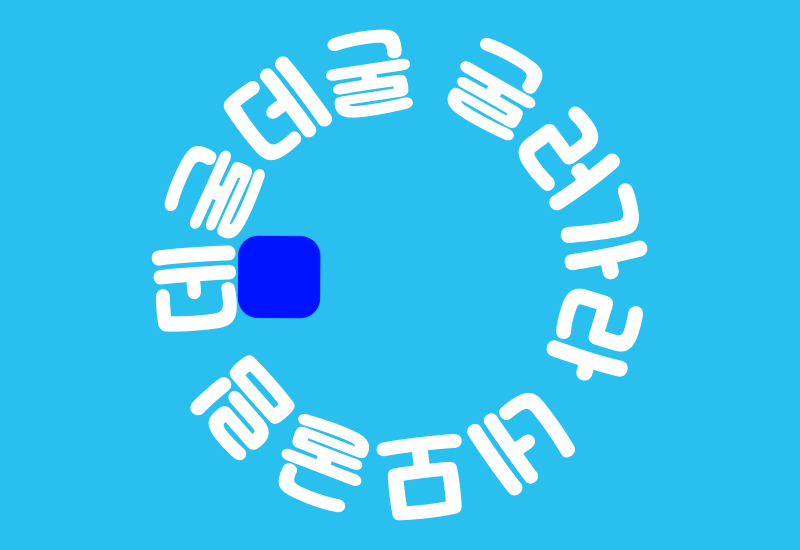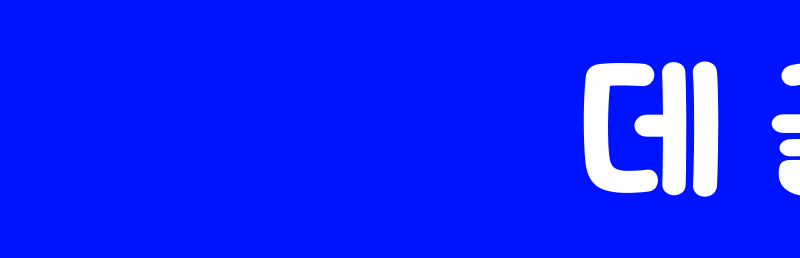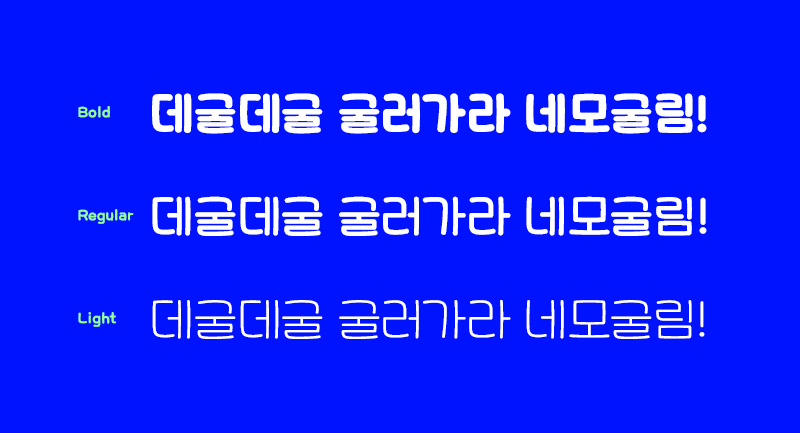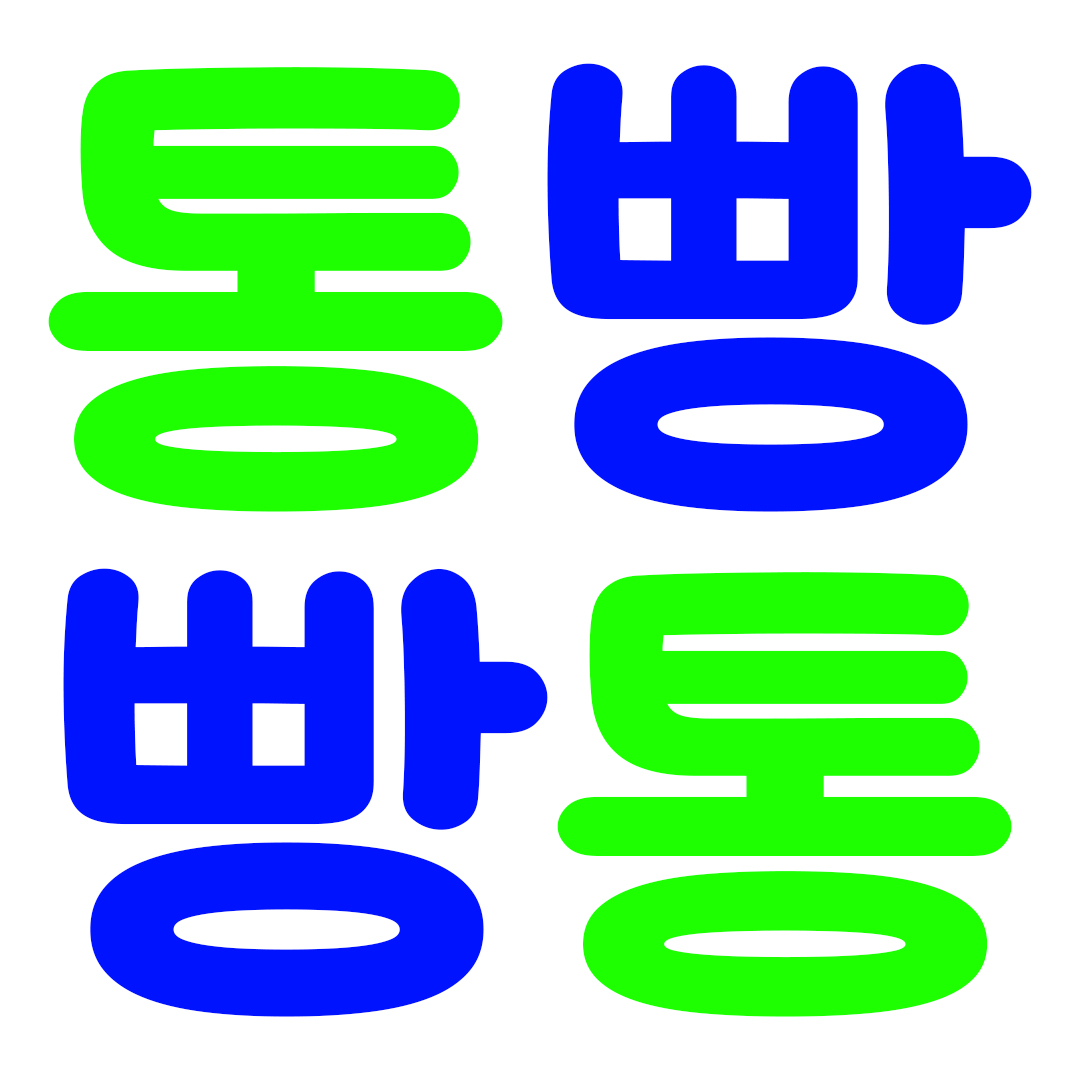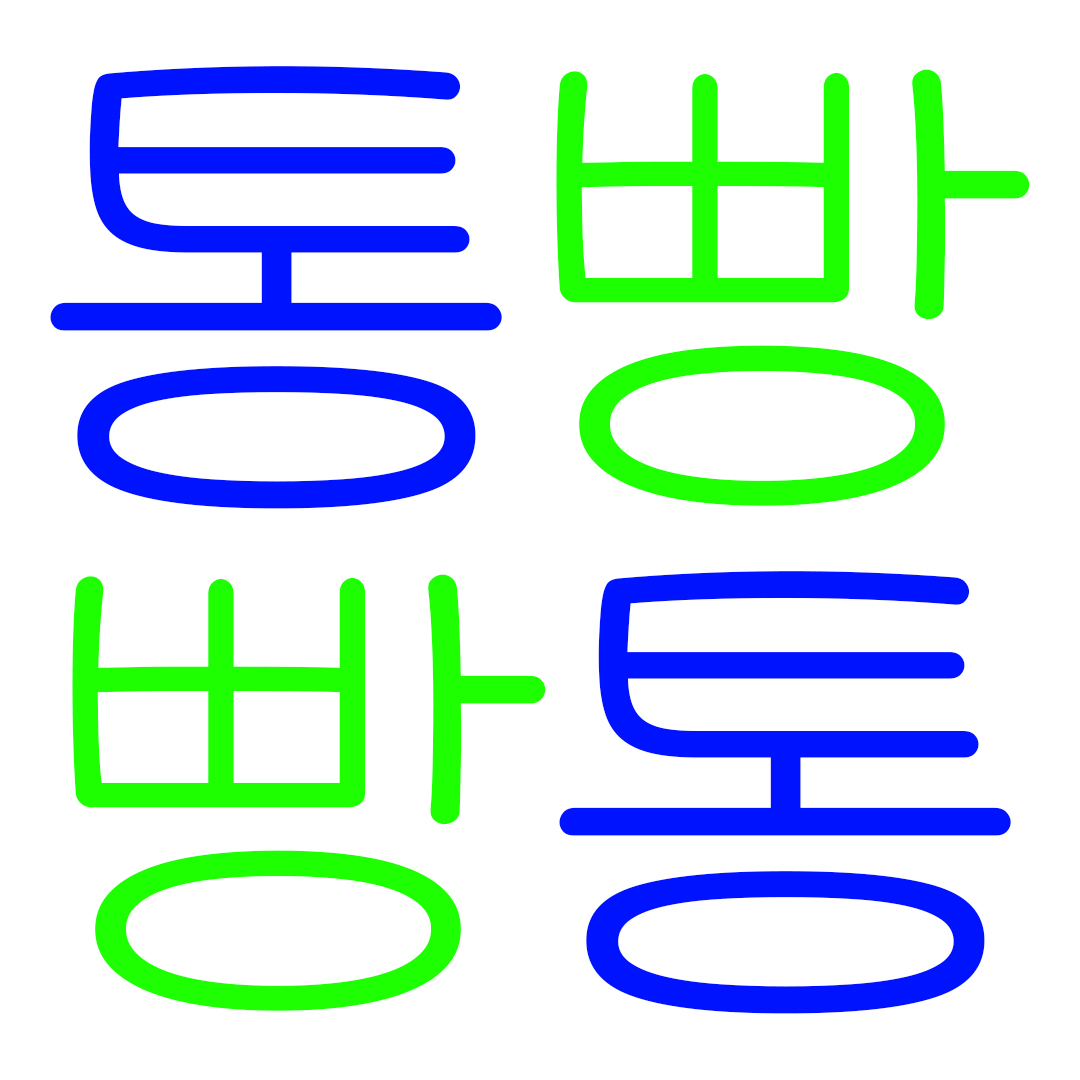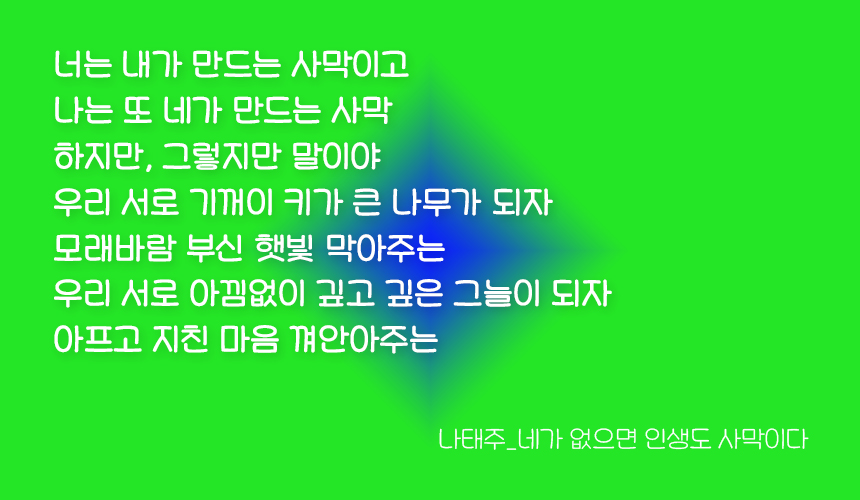
안녕하세요. 정갈한 고딕에 부드러운 굴림을 더한 2월의 신서체, 「Rix네모굴림」을 소개합니다. 데굴데굴 굴러가는 네모의 모습에서 착안해 디자인한 서체인데요, 각이 있는 부분에 굴림을 넣어 전체적으로 텐션이 느껴지는 귀여운 서체입니다. 폰트를 제작한 이수하 디자이너와의 인터뷰를 통해 더 자세히 알아볼게요!
이번에 제작하신 'Rix네모굴림 '서체에 대해 간단히 소개 부탁드려요.
Rix네모굴림은 꽉 찬 사각형 모듈에 데굴데굴 굴러가는 네모의 모습을 상상하며 만든 폰트입니다. 꺾이는 부분은 굴림을 넣어 네모가 잘 굴러가도록 한 점이 특징인 귀여운 제목용 서체입니다.
얘기만 들어도 굉장히 흥미로운데요, 작업 과정이 궁금한데 살짝 알려주실 수 있을까요?
Rix네모굴림은 Light > Bold > Regular 순서로 라이트를 기준으로 제작된 폰트라 굵기 파생을 할 때 볼드는 공간감과 회색도를 생각해 ‘ㅎ’ 종성의 모양을 다르게 제작했습니다.
폰트를 사용하는 분들이 이 부분은 꼭 알아줬으면 좋겠다! 하는 포인트가 있다면?
Rix네모굴림은 텐션에 대한 고민을 많이 한 폰트입니다. 사각형 골격이 망가지지 않고 텐션을 넣어 빵빵한 느낌을 낼 수 있는 방법을 찾다 안으로 갈수록 펴지고 밖으로 갈수록 텐션을 넣는 규칙을 찾았습니다. 이 규칙을 알고 보시면 네모굴림이 더 재밌을 거라 생각합니다~!
◆ 같은 폰트 다른 느낌
Rix네모굴림은 이름처럼 네모난 형태에 모서리가 둥굴린 듯 다듬어진 모습을 띄고 있습니다. 위와 같이 총 3가지 웨이트로 파생되어 높은 활용도를 갖고 있죠. 네모굴림 서체는 굵기에 따라 분위기가 사뭇 달라지는 특징이 있는데요😮
네모굴림 Bold는 두툼한 굵기에 굉장히 귀엽고 텐션이 느껴지는 헤드라인 글꼴인데, Light 두께로 쓸 경우 한 층 가볍고 깔끔하면서 정돈된 느낌을 주어 본문용으로 쓰기에도 좋습니다.
볼드와 라이트의 중간 굵기인 Regular는 적당한 굵기로 타이틀, 부제목, 본문까지도 폭넓게 사용할 수 있습니다.
■ 귀엽고 친근한 네모 글꼴
글자를 보면 가운데 직선적인 획들이 중심을 단단하게 잡아주고, 바깥쪽으로 갈수록 텐션을 넣어 전체적으로 빵빵하고 귀여운 네모굴림만의 특징을 갖도록 했습니다. 동글동글한 손글씨 느낌으로 친근한 이미지를 줄 수 있습니다.
두꺼운 굵기로 쓴 텍스트를 보면 귀여운 인상이 더욱 도드라지는 것을 볼 수 있는데요! 안정적인 글줄로 정돈된 느낌을 주면서도 통통한 획으로 사랑스러운 매력을 느낄 수 있는 서체입니다.
♣ 다채로운 활용법
Rix네모굴림 서체를 활용하여 디자인의 퀄리티를 높여보세요. 귀염뽀짝 특별한 연하장 카드를 받는 순간 행복 그 자체!
동글동글 귀여운 네모굴림 Bold체를 활용해 영상의 자막, 타이틀이나 스티커 등 굿즈에 사용하는 폰트로도 활용하기 좋아요. 글자 스타일 덕분에 보는 이에게 부드럽고 친근한 인상을 줄 수 있죠. 먼 거리에서도 눈에 확 띌 수 있는 두꺼운 굵기로 주목도가 높은 부분을 디자인에 활용해 보세요:)
오늘은 일상에 귀여움 한 스푼 얹어줄 헤드라인 폰트 Rix네모굴림을 만나봤는데요. 여러 웨이트로 제작되어 헤드라인 폰트로서의 활용뿐 아니라 본문 텍스트, 영상 자막, 인쇄물, 배너 등 폭넓게 활용하기 좋은 서체입니다. 앞으로 다양한 콘텐츠에서 발견되길 기대하며, 릭스폰트는 또 새로운 서체와 함께 돌아오겠습니다! 감사합니다✨